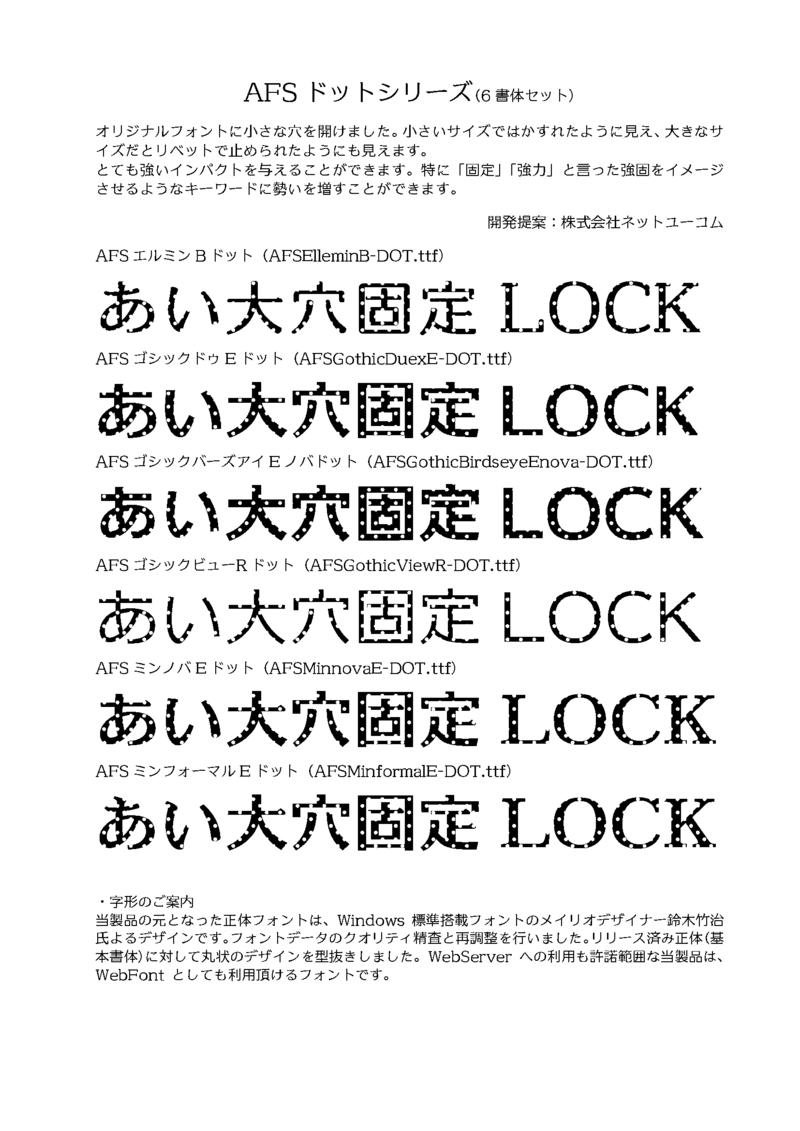
ネットユーコムからリリースされるフォントは目的限定フォント。
オリジナルフォントに小さな穴を開けました。小さいサイズではかすれたように見え、大きなサイズだとリベットで止められたようにも見えます。
とても強いインパクトを与えることができます。特に「固定」「強力」と言った強固をイメージさせるようなキーワードに勢いを増すことができます。